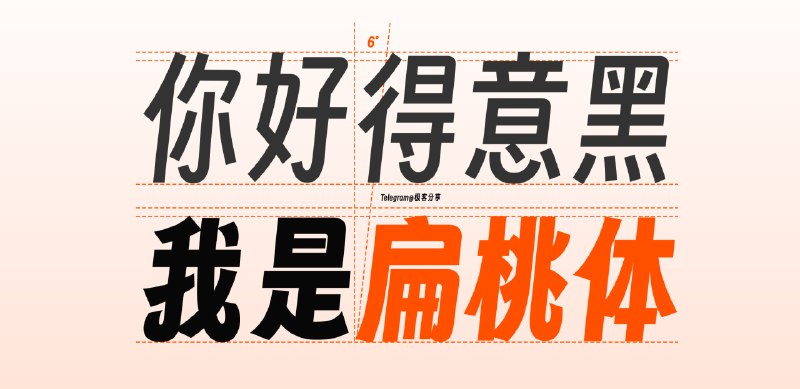
📝 Free Font 商用免费字体
Free Font 收录了 927 个可商用免费字体,可免费下载使用
📝 开源等宽字体 Maple Mono 发布 v7.0 正式版
Maple Mono 是一款开源等宽字体,专注于优化您的编码体验。
🅰缝合像素字体 - 开源的泛中日韩像素字体
📄由于使用多个像素字体合并而成,因此以「缝合」命名
📖方舟像素字体 - 一款免费开源的泛中日韩像素字体
📄支持拉丁语、简中、繁中、日语、Korean language 共 5 种字形;同时支持 10、12、16像素
还挺好看的🤩
📚免费商用字体库
📄主要面向中国大陆使用的免费商用字体库,每一个字体都经过严格筛选,最大程度上避免侵权风险并做到可追溯可验证。
🌐点击「Open in Figma」即可进入主页面,左侧有字体目录,每个页面都有介绍和下载链接
🆎中文网字计划 - 为网站开发者提供中文 Web Fonts 服务
📄中文网字计划通过精巧设计的字体分包方式,将庞大的字体文件切割为多个小型静态分包部署于云端,在全网领域内都可快捷、稳定地进行加载
从而可以通过网页加载本地没有的字体,实现更加美观的网页文字排版
✏️字魂扁桃体 - 一款开源免费可商用字体
📄字魂网对 oooooohmygosh 老师与锚钨团队发布了免费商用字体「得意黑」之上进行二次创作
发布开源免费可商用字体「字魂扁桃体」
名字很有特色,希望再出个脑垂体什么的
®️360查字体 - 一个查询字体版权的工具
🌐分享几个字体下载网站
0️⃣猫啃网:5500+免费可商用字体,无套路下载
1️⃣字体家:有免费和付费,免费部分可无套路下载
2️⃣字体天下:有免费和付费,免费部分可无套路下载
✏️noMeiryoUI - 一款全局更换Windows字体的小工具
📃这个小工具是由一位小日子过得不错的人开发的,界面简单
支持全局更换字体,也支持部分更换,当然也可以恢复默认
✏️100font - 一个专门收集整理免费商用字体的网站
✏️字体空间 - 一个提供10w+免费英文字体下载的网站,另外还支持输入文字生成字体、字符表情生成
✏️nexusfont - 一款免费的Windows字体管理软件
📃昨天看到很多自媒体在推一个开源字体得意黑,我也下载回来体验了一番,确实不错!
但是发现每次打开PS的时候一大堆字体不知从何下手,于是遍稍微找了一下字体管理软件,发现这款非常简单美观且实用软件,大家可以试试!
此外,这个来自韩国的开发者还有几款不错的免费软件在同个页面。
nexusfont - 一款免费的字体管理软件,配合之前推荐过的免费字体下载网站猫啃网,可以实现一站式全免费管理 #字体 。支持中文,这个网站还有其他几款免费软件,感兴趣的可以试试。
猫啃网 - 免费商用中英文 #字体